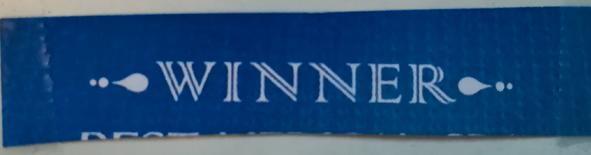
Suche Logo-Schrift aus einem Print-Magazin
ich suche diese (oder auch eine ähnliche) Schrift, welche ich in einem Magazin für Gartenmöbel gefunden habe. Es geht mir vorallem um die "Doppellinien" dieses Schriftzuges!
Colonna. Ist in Microsoft Office 2016 enthalten.
Super, vielen Dank für die rasche Antwort. Kennt ihr auch noch ähnliche Schriften?